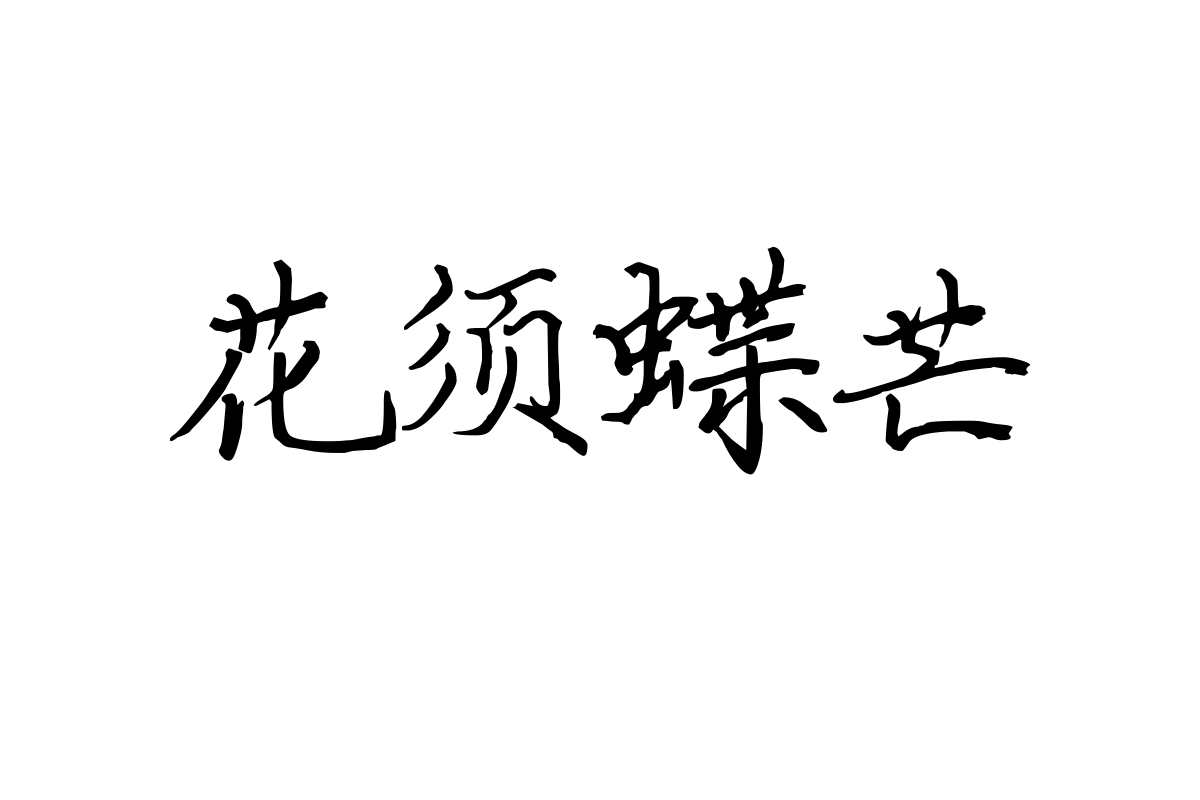
段宁硬笔楷书是一种具有独特韵味的书法字体,以其流畅、清晰、有力的笔触而闻名。这种字体的特点是笔画粗细均匀,线条流畅自然,给人一种简洁明快的感觉。同时,由于其硬笔书写的特点,使得字体显得更加有力和有力。
在结构上,段宁硬笔楷书采用了传统的楷书结构,包括横、竖、撇、捺等基本笔画。每个字的笔画都遵循一定的规则和顺序,使得整个字体看起来整齐划一。此外,这种字体还注重字形的变化和组合,使得整个作品既有规律又富有变化,给人以美的享受。
总的来说,段宁硬笔楷书是一种既具有传统韵味又不失现代感的书法字体,适合用于各种场合,如书籍、报纸、海报等。